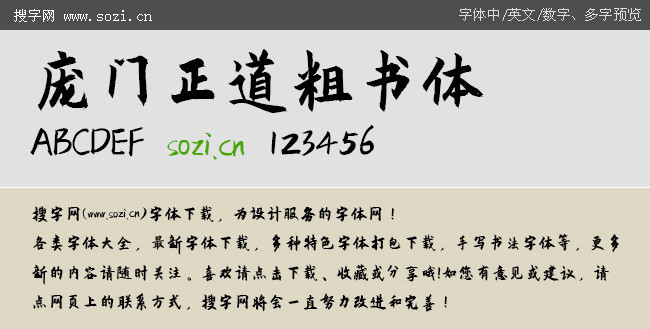
龐門正道粗書體
搜字網(wǎng)給大家提供一款龐門正道粗書體中文字體下載,龐門正道粗書體是一款不錯的手寫藝術(shù)字體,這款字體筆觸較為粗實(shí),書寫端正大氣,重要的是可以免費(fèi)商用,適合應(yīng)用于藝術(shù)設(shè)計(jì)、平面宣傳設(shè)計(jì)、網(wǎng)頁設(shè)計(jì)、海報(bào)設(shè)計(jì)等應(yīng)用。